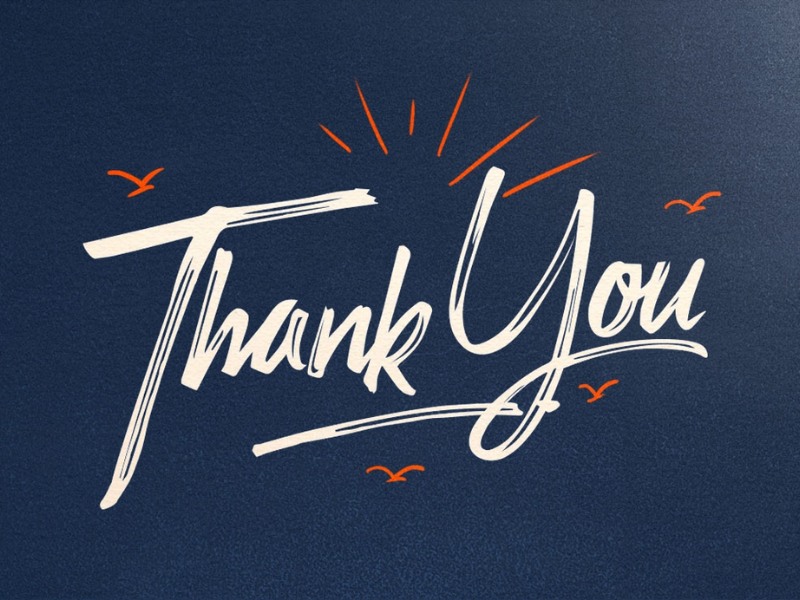
Trong thế giới đồ họa hiện đại, phong cách chữ viết tay bằng cọ vẽ luôn mang đến một sức hút đặc biệt nhờ vẻ ngoài phóng khoáng và giàu tính nghệ thuật. Font brush Việt hóa là công cụ hữu ích giúp người thiết kế truyền tải những thông điệp mang đậm dấu ấn cá nhân, sự sáng tạo và năng động.
Đặc điểm ấn tượng của các dòng font brush Việt hóa
Dòng font này mô phỏng chân thực những nét cọ quét thô mộc, tạo nên các hiệu ứng nhám, vết mực loang hoặc những đường xước tự nhiên trên bề mặt chữ. Khác với các kiểu chữ hệ thống cứng nhắc, font chữ brush Việt hóa mang lại cảm giác sinh động và có chiều sâu thị giác hơn. Việc Việt hóa kỹ lưỡng giúp các ký tự có dấu như “ă, ê, ơ, ư” hay các dấu thanh phối hợp nhịp nhàng với độ rung của nét cọ, tránh tình trạng lỗi font gây mất thẩm mỹ.
Bên cạnh đó, cấu trúc của các bộ font brush thường khá linh hoạt với độ đậm nhạt không đồng nhất. Điều này giúp tạo ra nhịp điệu cho văn bản, khiến người xem cảm thấy sự gần gũi như được viết bằng tay thủ công. Đây là phương án hiệu quả để thu hút sự chú ý và khơi gợi cảm xúc mạnh mẽ cho khách hàng ngay từ những giây đầu tiên nhìn thấy bản thiết kế.
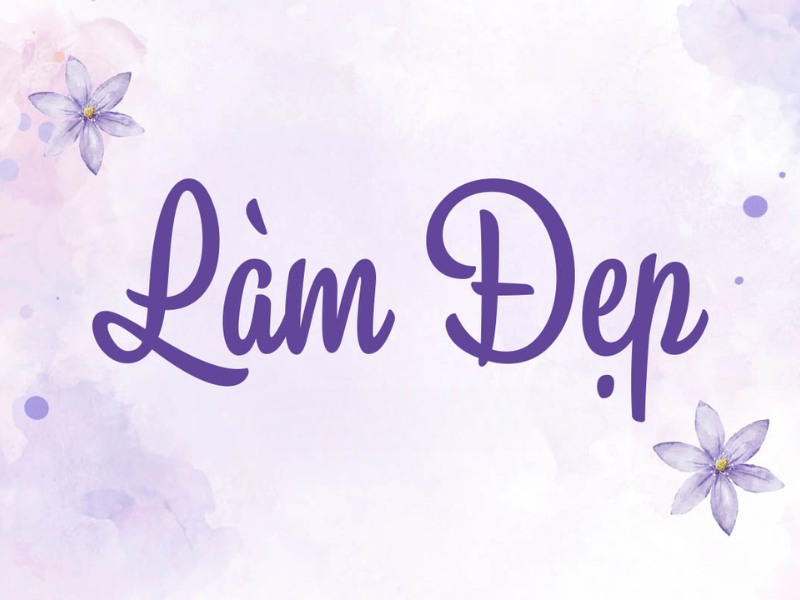
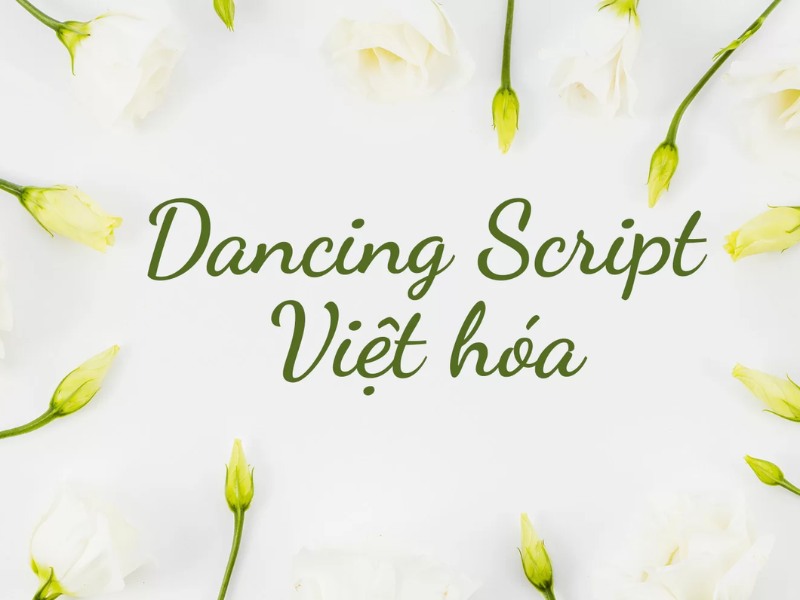
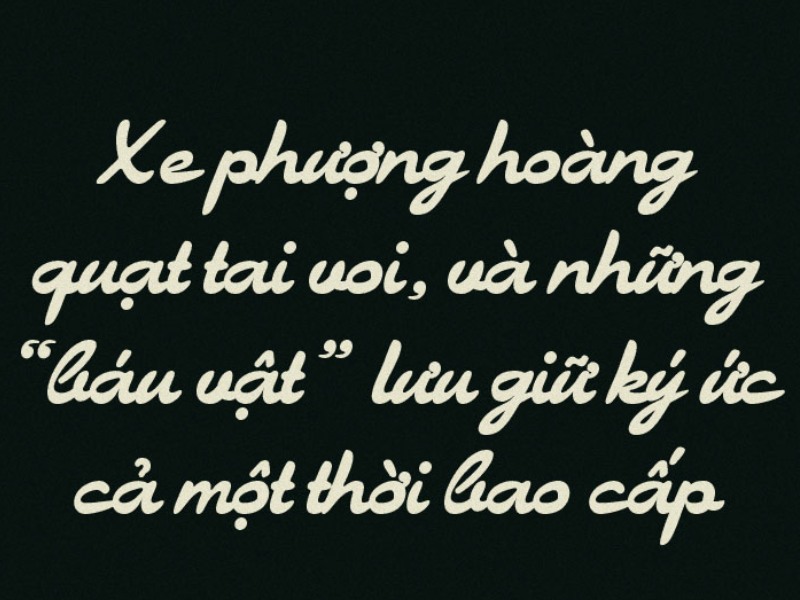
Gợi ý phối hợp: Font brush có cá tính rất mạnh và nét chữ dày. Để tổng thể thiết kế hài hòa, bạn nên phối hợp font chữ nét cọ Việt hóa với một font không chân (Sans-serif) đơn giản cho phần thông tin chi tiết. Sự tương phản này sẽ giúp tiêu đề chính của bạn trở nên nổi bật và dễ đọc hơn.
03 Ứng dụng font chữ brush Việt hóa vào thiết kế kiến trúc
Nhờ vẻ ngoài phóng khoáng và tự nhiên, bộ font chữ này mang lại giá trị cao khi được đưa vào thực tế trang trí và quảng bá các công trình hiện đại:
- Bảng hiệu cho Homestay và Quán Cafe: Những nét cọ thô mộc của font brush rất ăn ý khi xuất hiện trên chất liệu gỗ kẽm hoặc alu phủ màu. Đối với các dự án nhà lắp ghép dành cho nghỉ dưỡng, font chữ này giúp tạo nên phong cách rustic, mộc mạc và thân thiện.
- Thiết kế Poster quảng bá nhà container: Sử dụng font brush cho các tiêu đề chính trên banner quảng cáo giúp khơi gợi cảm hứng về một lối sống tự do, không khuôn khổ, rất dễ tạo thiện cảm với nhóm đối khách hàng trẻ.
- Trang trí nội thất và Slogan tường: Bạn có thể dùng font này để cắt chữ nổi laser hoặc vẽ trực tiếp lên tường trong các căn hộ, văn phòng sáng tạo. Nét chữ nét cọ sẽ làm giảm bớt sự khô khan của các mảng khối xây dựng, mang lại sức sống cho không gian.
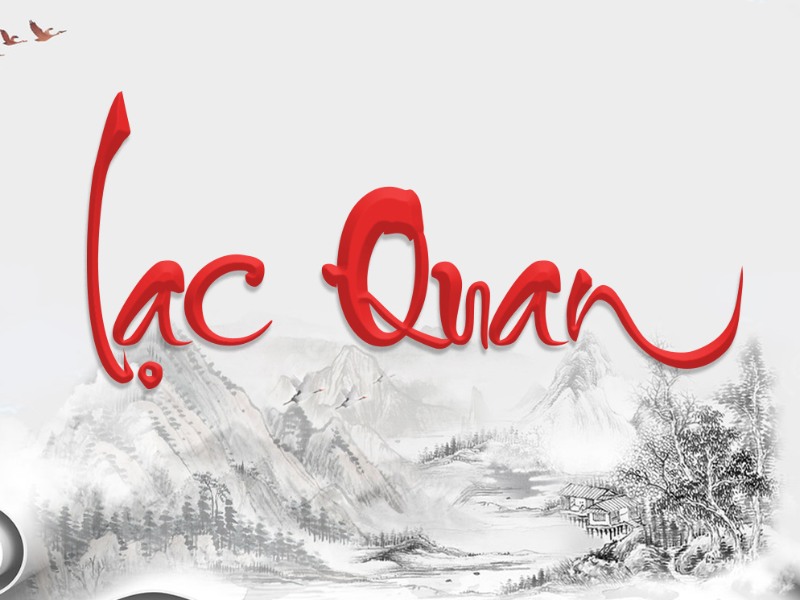
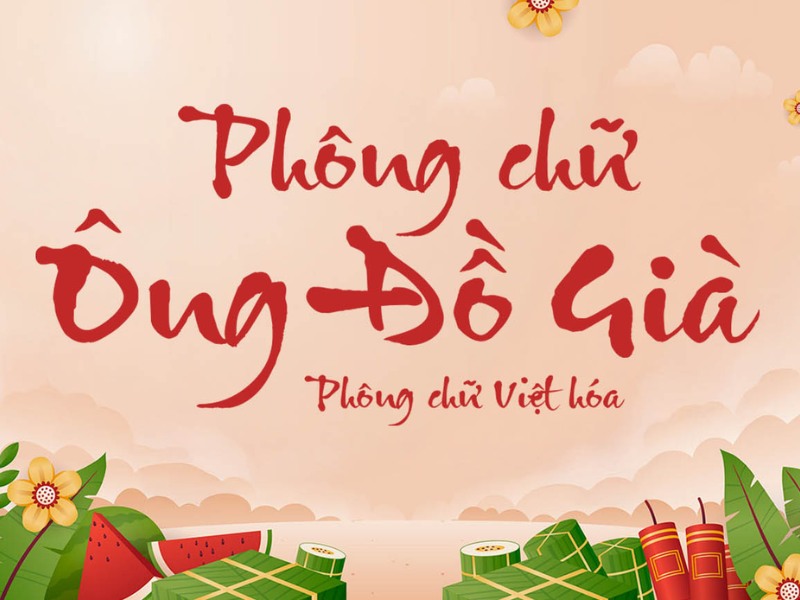
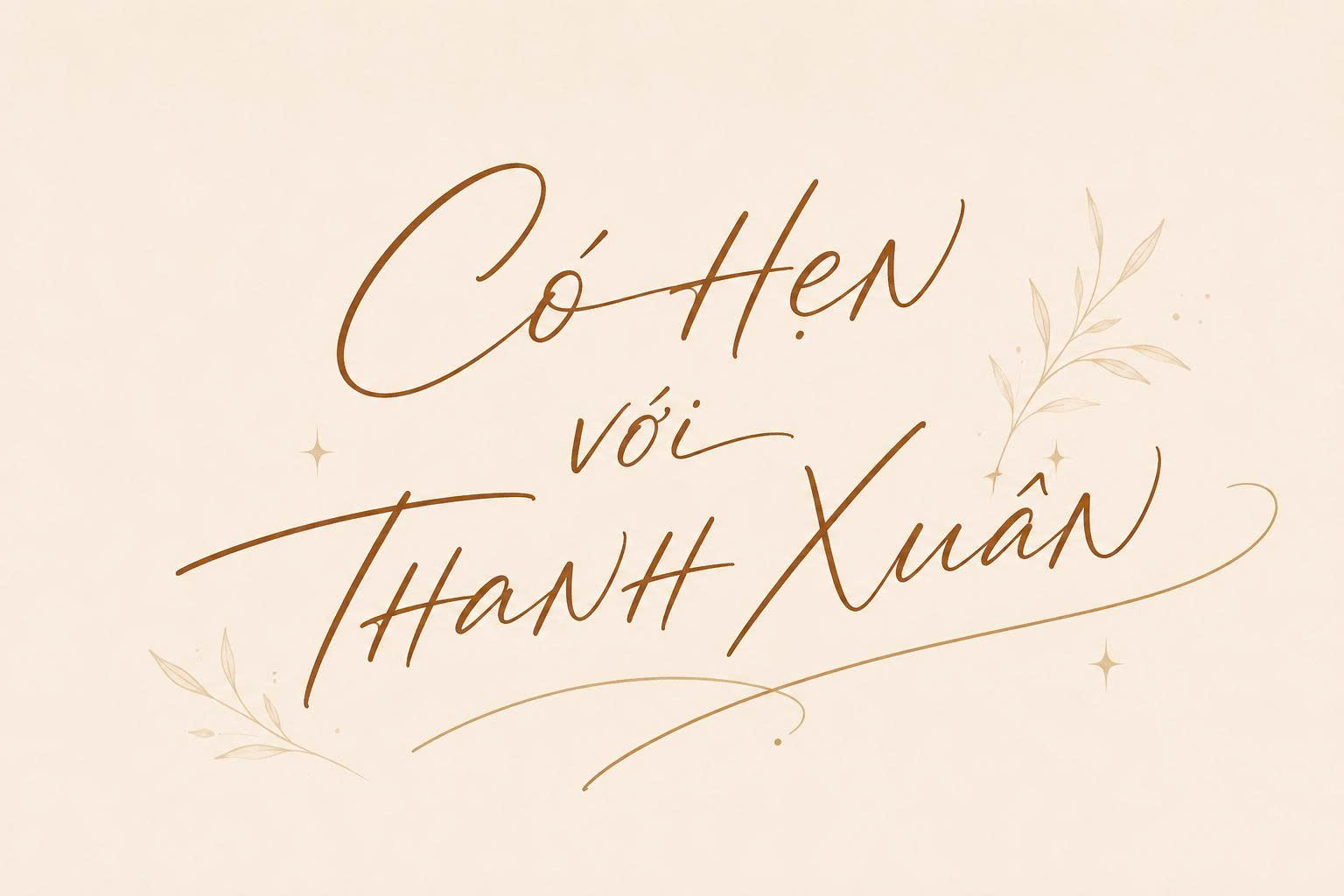
03 số lưu ý khi sử dụng font brush Việt hóa để bố cục chuyên nghiệp
Để khai thác hiệu quả vẻ đẹp của font chữ nét cọ Việt hóa mà không làm rối mắt người đọc, người thiết kế nên lưu tâm một số điểm sau:
- Hạn chế viết hoa toàn bộ: Đa số các font brush có nét nối chữ thường rất đẹp, việc sử dụng toàn bộ chữ in hoa có thể làm mất đi tính nhịp điệu và gây khó đọc.
- Kiểm soát độ tương phản màu sắc: Do font có nhiều chi tiết vết xước nhỏ, bạn nên đặt chữ trên nền màu đơn giản hoặc có độ tương phản rõ rệt để các nét cọ không bị nhòe khi hiển thị trên màn hình.
- Tránh dùng cho văn bản dài: Chỉ nên sử dụng font brush cho tiêu đề, slogan hoặc các câu trích dẫn ngắn. Sử dụng cho đoạn văn bản dài sẽ gây mỏi mắt và làm mất đi tính chuyên nghiệp của hồ sơ thiết kế.